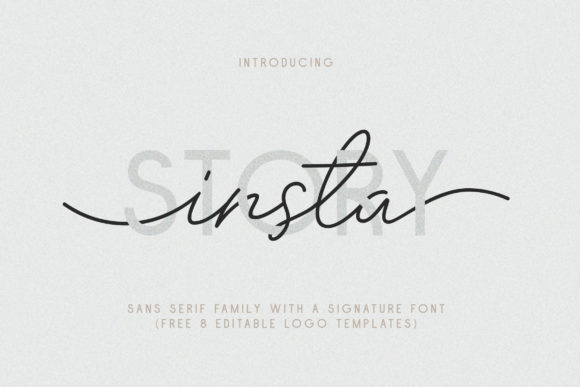
Insta Story Duo
適切なデザイン要素を見つけるのは難しい場合がありますが、Insta Story Duoは作品を即座に引き立てる優れたコレクションを提供します。
POD(オンデマンド印刷)製品、結婚式の招待状、またはソーシャルメディアのグラフィックを作成している場合でも、Insta Story Duoは理想的です。